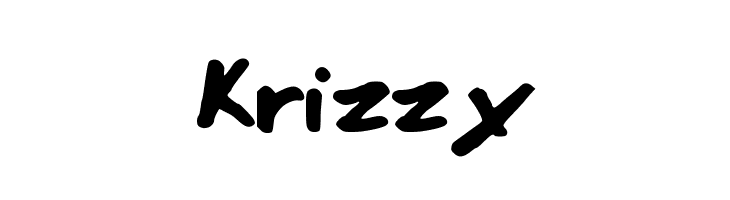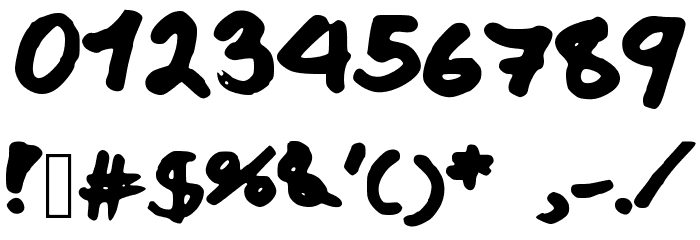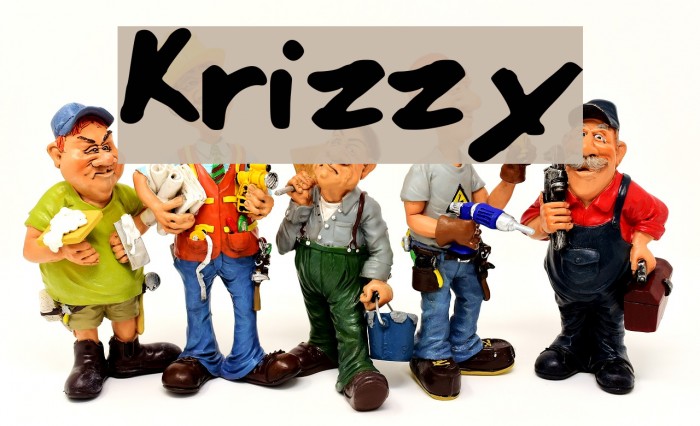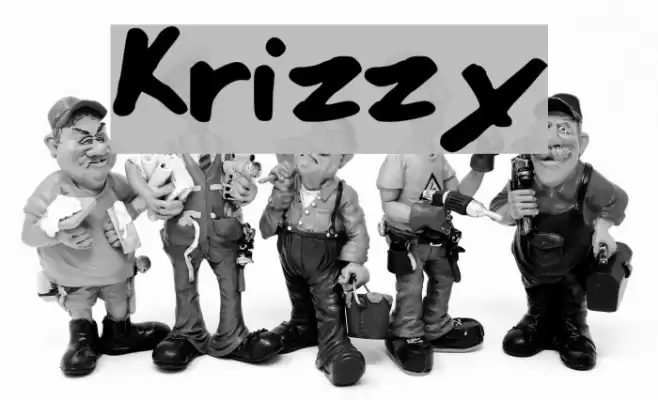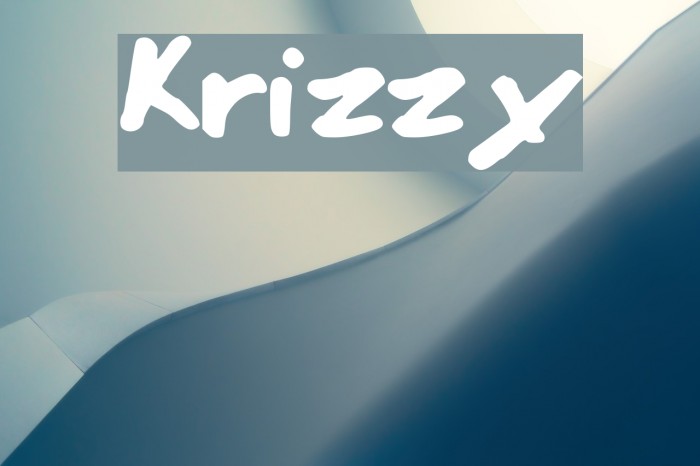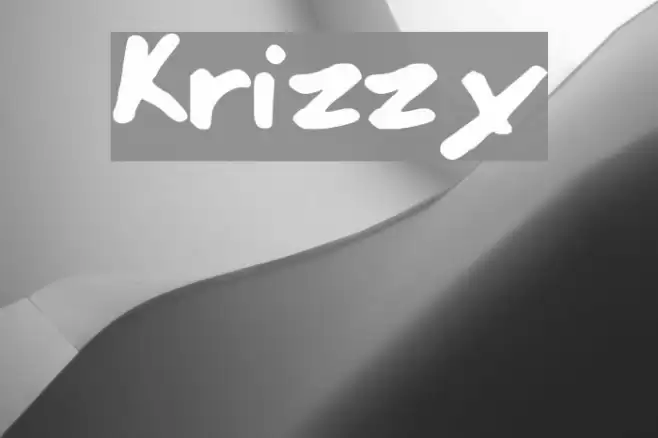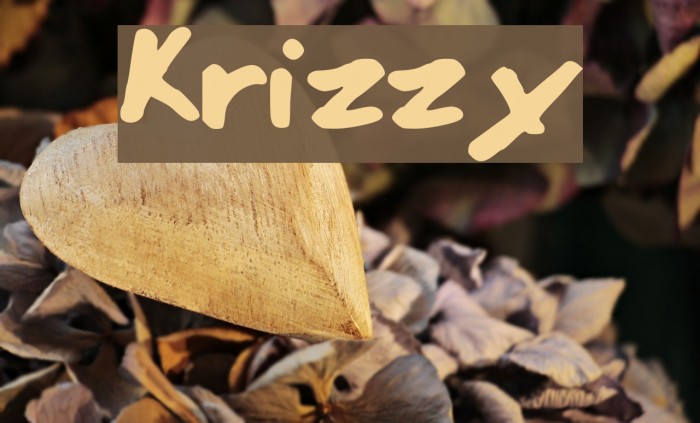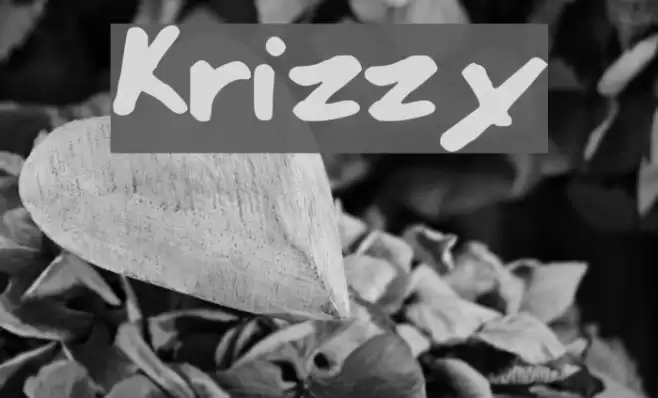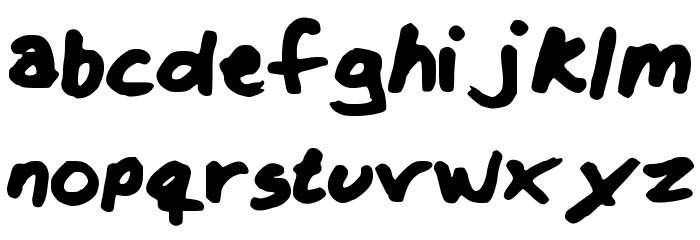
Krizzy Font
| Gesamtstil | Playful |
| Anwendungsfall | Logos, Headlines, Informal Text |
| Vorgeschlagene Projekte | Ideal for children's books, greeting cards, playful branding, and casual invitations. |